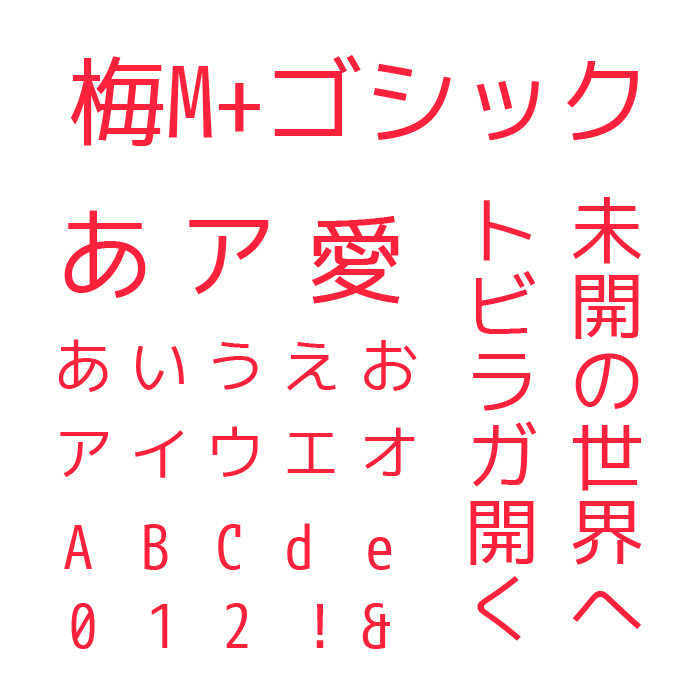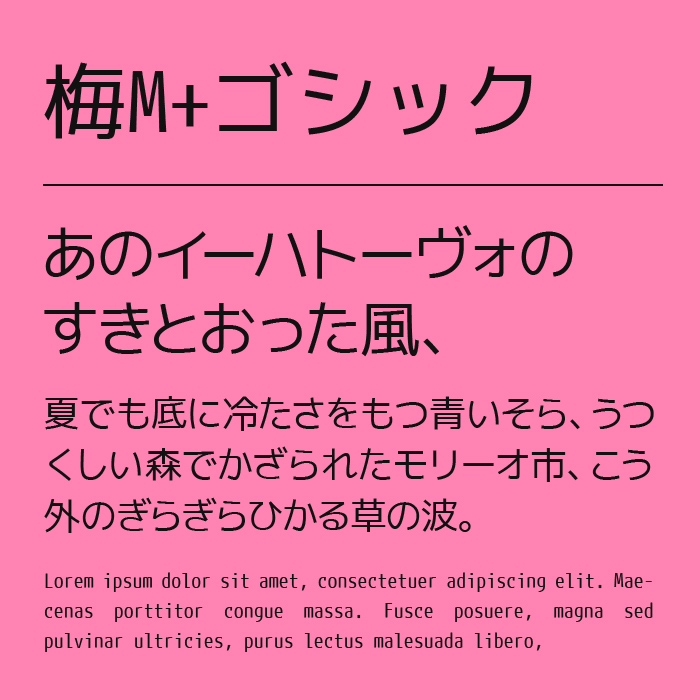
梅M+ゴシックは、明瞭で端正な構成が魅力の梅ゴシックにM+フォントを合成したゴシック体フォントです。
シンプルながらも骨格がしっかりとしており、可読性と洗練された印象のバランスのよいフォントです。
細めのウェイトながら視認性が高く、スマートで軽快な印象を与えるため、ナチュラルで上品な文章表現にもフィットします。可愛すぎず、固すぎないデザインは、汎用性を求める場面やビジネスシーンなどでとても重宝するゴシックフォントです。